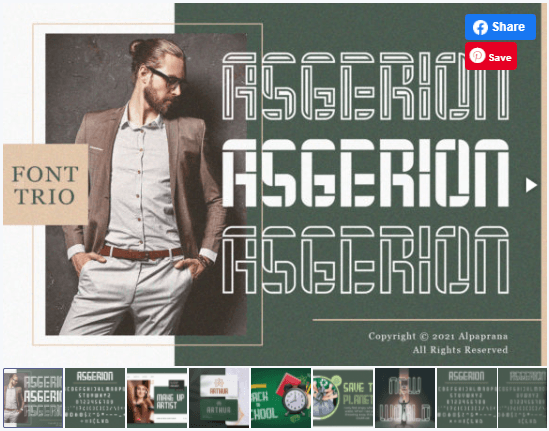
Asgerion Font
Asgerion - роскошный и напористый дисплейный шрифт. Этот шрифт идеально подходит для написания веб-дизайнов, визитных карточек и всего остального, что требует уникального подхода.